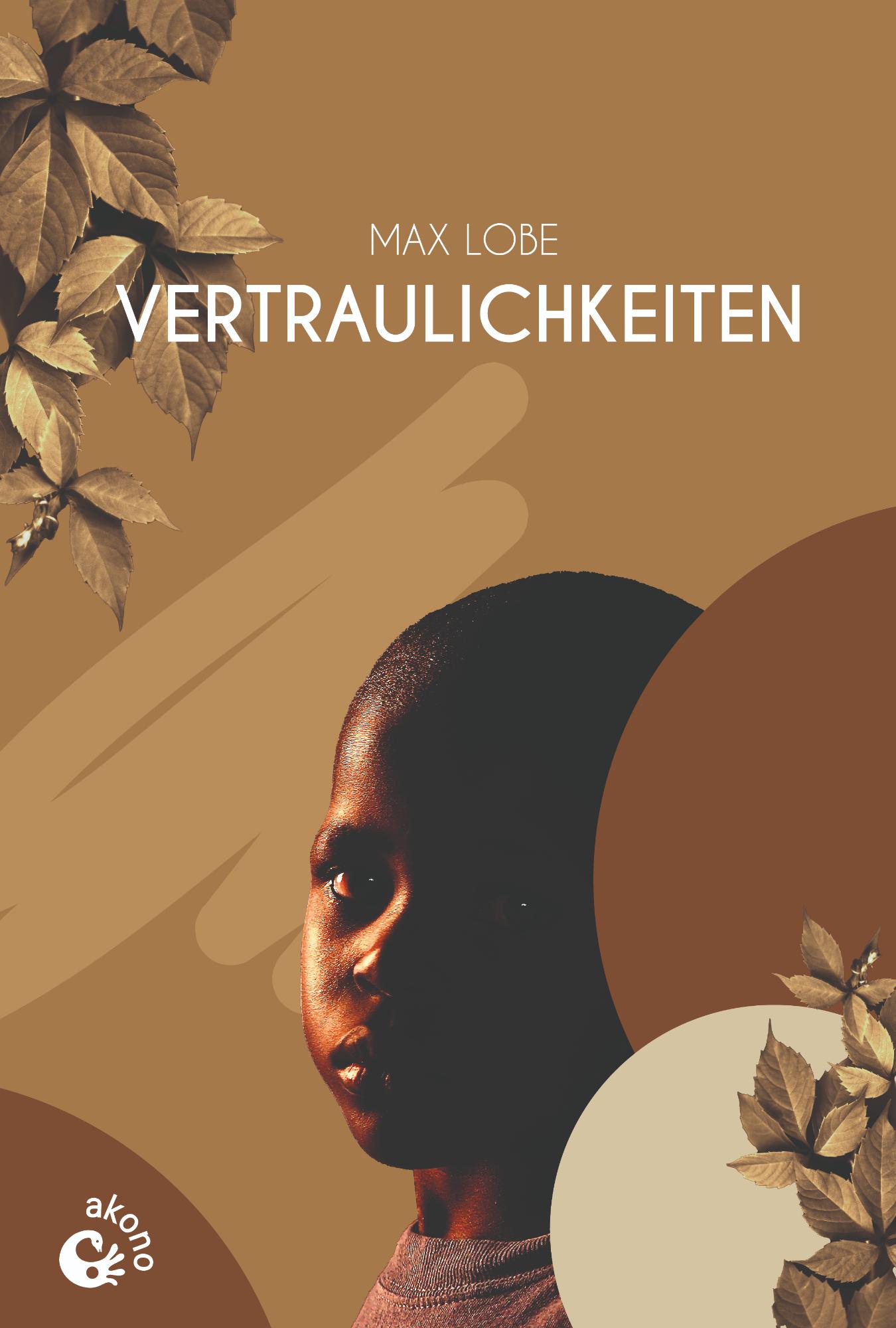
Suche Schriftart eines Buchcovers (Vertraulichkeiten)
bin aktuell auf der Suche nach der Schriftart des Buchcovers "Vertraulichkeiten" von Max Lobe. Das Buch erscheint am 15. August 2022 als Taschenbuch bei Akono Verlag.
2022, das ist erstaunlich. Da hat der Gestalter zwei Zeilen in Versalien zu setzen und versemmelt die Sache komplett.
Klar: langes Wort, großer Schriftgrad, sehr breites O und C. Dann wird spationieren problematisch. Und trotzdem wäre in Sekunden ein besserer Ausgleich möglich gewesen.
Lücke nach dem V und um das T und – vor allem – das K steht viel zu dicht am H und zu weit vom E weg.
Schade.